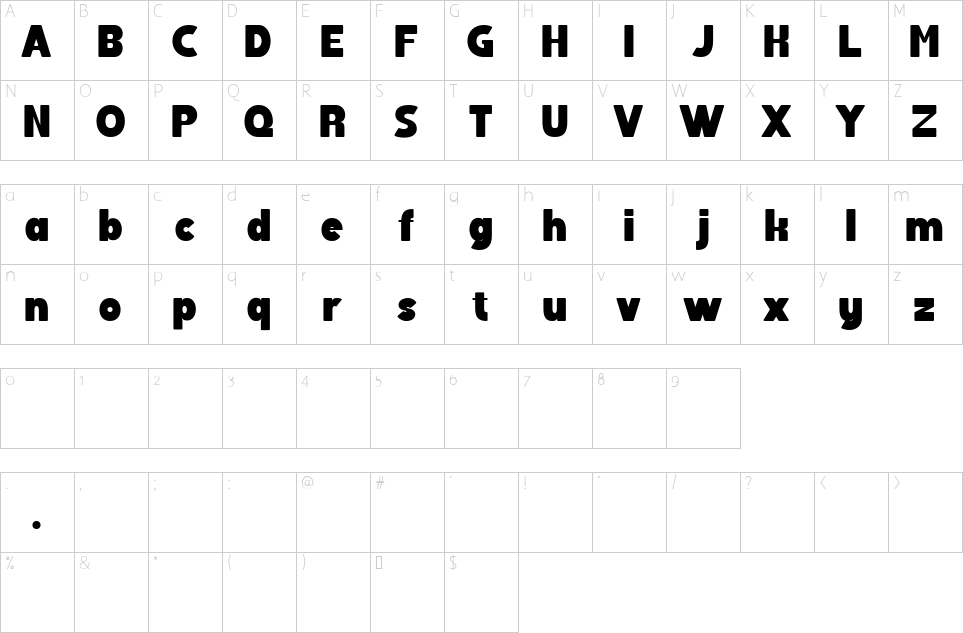
Descubra a elegância moderna do Gruno Font, uma oferta gratuita disponível tanto para Windows quanto para Mac. Desenvolvida por Flawless And Co, esta fonte recebeu 501 downloads desde sua disponibilização. Com seu design minimalista e sofisticado, o Gruno é perfeito para aplicativos de texto, publicações digitais ou até mesmo como um ponto de encontro da sua identidade visual personalizada. Aproveite essa oportunidade de adquirir uma fonte sem custos adicionais que combina elegância com praticidade. Instale já e explore o poder de expressão do Gruno.